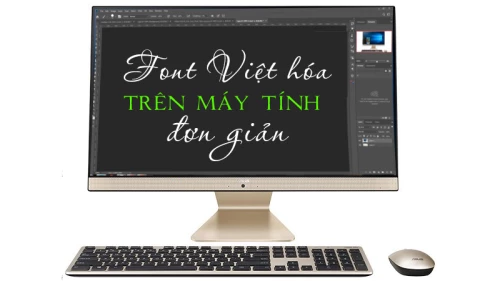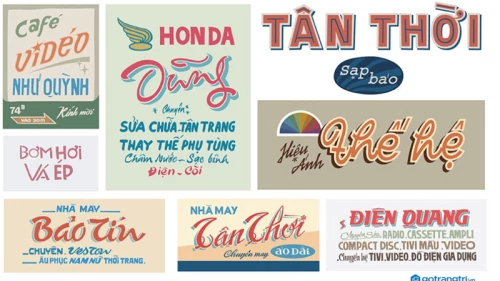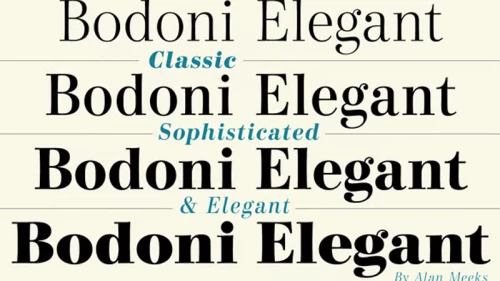
Cách tải và sử dụng Font Việt hóa trên máy tính đơn giản và hiệu quả nhất
Tại Việt Nam, các Designer rất hay gặp một số khó khăn khi muốn sử dụng font chữ đẹp vì thông thường các phần mềm chỉnh sửa ảnh sẽ không hỗ trợ các ký tự có dấu của tiếng Việt. Nếu bạn muốn sử dụng các font chữ này thì sẽ mất khá nhiều thời gian chỉnh sửa bỏ dấu và các ký tự bị lỗi. Vì vậy, trong bài viết dưới đây trangcongnghe.vn sẽ bật mí cho các bạn cách tải font Việt Hoá trên máy tính đơn giản và hiệu quả nhất.
Tại sao nên sử dụng Font Việt hóa trên máy tính?
Đối với nhà Designer chuyên nghiệp thì sẽ sử dụng các bộ font máy tính có sẵn như: Unicode, VNI, UTM,… Đây là những font chữ cơ bản sẽ không thể giúp bạn hài lòng và nếu bạn sử dụng từ ảnh đến ảnh khác, sẽ bị nhàm chán vì vậy font Việt Hoá rất được các nhà thiết kế chuyên nghiệp đón nhận.
Font chữ này, không chỉ mang đến cho bạn muôn vàn sự lựa chọn mà còn cho ra một sản phẩm chuyên nghiệp, sáng tạo. Do đó việc tải font và cài đặt các font chữ Việt Hoá đẹp trong Photoshop là cần thiết và quan trọng để bạn có thể tạo sự đặc biệt cho tác phẩm.
Tổng hợp Font Việt Hoá đẹp nhất dành cho photoshop
Font MINNA DROP
Minna Drop là Font chữ Việt Hoá tuy đơn giản nhưng vẫn mang đến phong cách cổ điển và thanh lịch. Vì vậy, rất phù hợp để thiết kế cho thiệp cưới, áp phích, banner về mỹ phẩm và quần áo nhờ đó, Minna Drop đang được người dùng đón nhận và sử dụng rộng rãi.
Font Classique Saigon
Classique Saigon là Font chữ mang đến phong cách hoài niệm về phong cách xưa. Font Việt Hoá này rất phù hợp thiết kế các ấn phẩm quảng cáo, áp phích, banner mang hơi hướng cổ điển, vintage. Nhờ đó, Classique Saigon là sự lựa chọn hàng đầu khi bạn muốn tải Font Việt Hóa dành cho Photoshop.
Font Coco FY
Coco FY là Font chữ được sử dụng nhiều trong thiết kế banner, biển quảng cáo, bao bì,... cho nhà hàng, công ty dịch vụ. Không những vậy, Coco FY được bo tròn các góc cạnh tạo nên cảm giác mềm mại, bay bổng nhưng vẫn rất hiện đại trong các tác phẩm thiết kế
Font Playlist Script
Trong list danh sách các font chữ đẹp không thể thiếu đó là Playlist Script. Font chữ này mang đến phong cách hiện đại khi thiết kế rất giống với chữ viết tay thường được sử dụng nhiều trong thiết kế logo, banner, bao bì, … Đây là font chữ rất phù hợp trong mọi thiết kế để bạn tham khảo.
Font Bodoni
Bodoni là Font chữ Việt Hoá rất ấn tượng khi thiết kế hình ảnh trên Photoshop. Font chữ này thoạt nhìn rất mềm mại nhưng nhìn kỹ lại sở hữu đường nét cứng cáp của Font máy tính truyền thống. Vì vậy, Font Bodoni luôn tạo được cảm giác dễ chịu cho người đọc và là sự lựa chọn hàng đầu khi thiết kế.
L’Hanoienne
Giống với Font chữ Classique Saigon ở trên, L’Hanoienne cũng được truyền cảm hứng từ Thủ đô Hà Nội cổ kính. Tuy font chữ này có nhiều nét tương đồng nhưng lại mang đến phong cách riêng thanh lịch, vintage nhưng không quá uỷ mị.